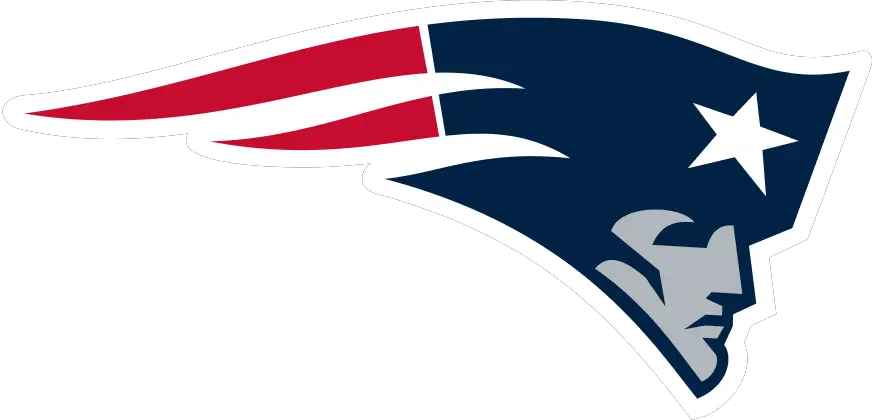
Fon Patriot
Diterbitkan: 2023-03-30Seperti yang kita semua tahu, Patriots telah menjadi salah satu tim paling sukses dalam sejarah olahraga profesional selama beberapa waktu, dan tak perlu dikatakan lagi bahwa identitas merek tim telah memainkan peran penting dalam kesuksesan mereka karena beberapa alasan yang telah terjadi. didokumentasikan secara luas selama bertahun-tahun.
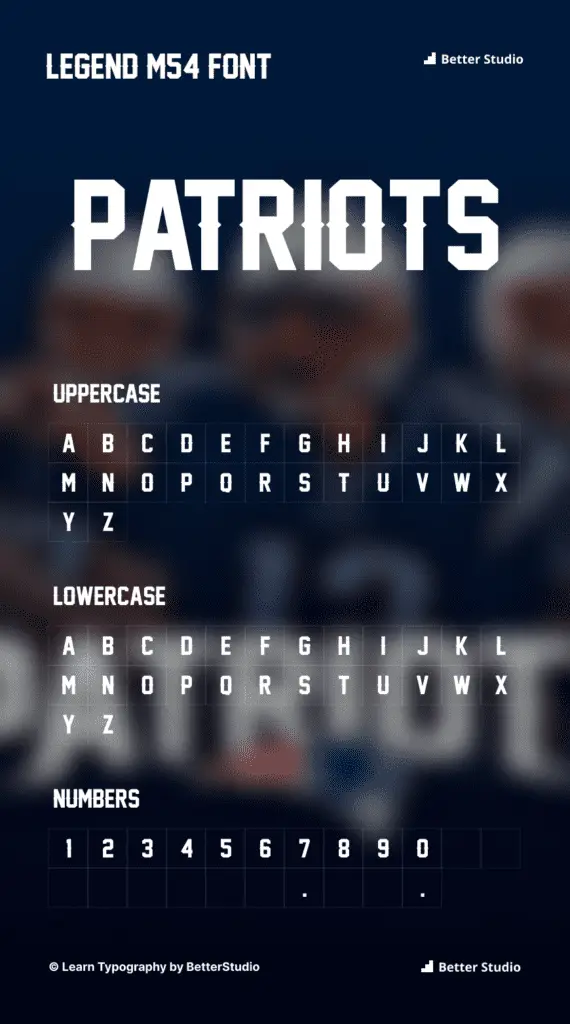
Font Apa yang Digunakan Logo Patriots?
Seperti yang Anda ketahui sekarang, logo Patriots menggunakan jenis huruf yang disebut " Legend M54 " Jenis huruf ini dirancang oleh seniman grafis Masanao Hirayama dan pertama kali dirilis pada tahun 2010 sebagai font resmi tim.
Font sans serif yang menarik dengan gaya sederhana dan minimalis, font ini bekerja sangat baik untuk menciptakan identitas merek karena kesederhanaan dan tampilannya yang ramping sehingga Anda tidak memerlukan generator font atau generator teks untuk menggunakannya.
Alternatif dan Gaya Font Mirip dengan Legend M54
Ada banyak font di luar sana yang memiliki kesamaan dengan keluarga font Legend M54 termasuk:
- Font Axis Ultra
- huruf Azri
- Font Regalia Pro
- Fon Furgatorio
- Fonta neutron
Seperti yang dapat Anda lihat dari contoh di bawah ini, masing-masing font ini memiliki gaya modern dan minimal yang menjadikannya sempurna untuk mendesain identitas merek untuk perusahaan dan merek. Pastikan untuk menambahkan "font" di akhir nama font saat mencarinya secara online.
Siapa yang Mendesain Font Patriots?
Ada seorang desainer tipe dari Tokyo, Jepang yang dikenal sebagai justme54s yang merupakan salah satu kontributor utama desain logo Patriots, dia mengkhususkan diri dalam mendesain tipografi.
Ada beberapa tipografi unik yang dia buat, termasuk tipografi Legend M54 yang terkenal yang menjadi identik dengan merek Patriots sebagai bagian dari karyanya.
Selain logo, sampul buku, dan bahkan font video game, Justme54s juga telah mengerjakan proyek lain yang tak terhitung jumlahnya selama bertahun-tahun.
Deskripsi Patriot
Ada tim sepak bola profesional Amerika bernama Patriots yang berbasis di Foxborough, Massachusetts, yang bermain di AFC East.
Didirikan pada tahun 1959, tim ini adalah bagian dari American Football League (AFL) dan berkompetisi di divisi Timur liga sebagai anggota American Football Conference (AFC).
Selain memenangkan enam kejuaraan Super Bowl, Patriots telah menciptakan ikon budaya olahraga dengan logo unik mereka.
Di antara ciri khas logo Patriots adalah font Legend M54, yang merupakan tipografi gaya kotak-kotak yang desainnya tebal dan kotak-kotak dan dimaksudkan untuk mewujudkan kekuatan dan kekuatan pada saat yang bersamaan.
Menggunakan font Legend M54 membuat logo Patriots terlihat tangguh, kuat, dan mengintimidasi karena kekuatan, dan tampilannya yang kokoh.
Sebagai simbol komitmen tim kami terhadap keunggulan, tulisan pada helm memainkan peran penting dalam menekankan komitmen dalam huruf tebal yang disertai dengan bintang putih untuk lebih menekankan gagasan bahwa mereka berkomitmen untuk keunggulan.
Seluruh desain dibingkai oleh bingkai melingkar, membuatnya langsung dapat dikenali dan diingat. Bersama-sama, font dan logo menciptakan pernyataan visual yang kuat yang secara tepat mencerminkan semangat Patriot.